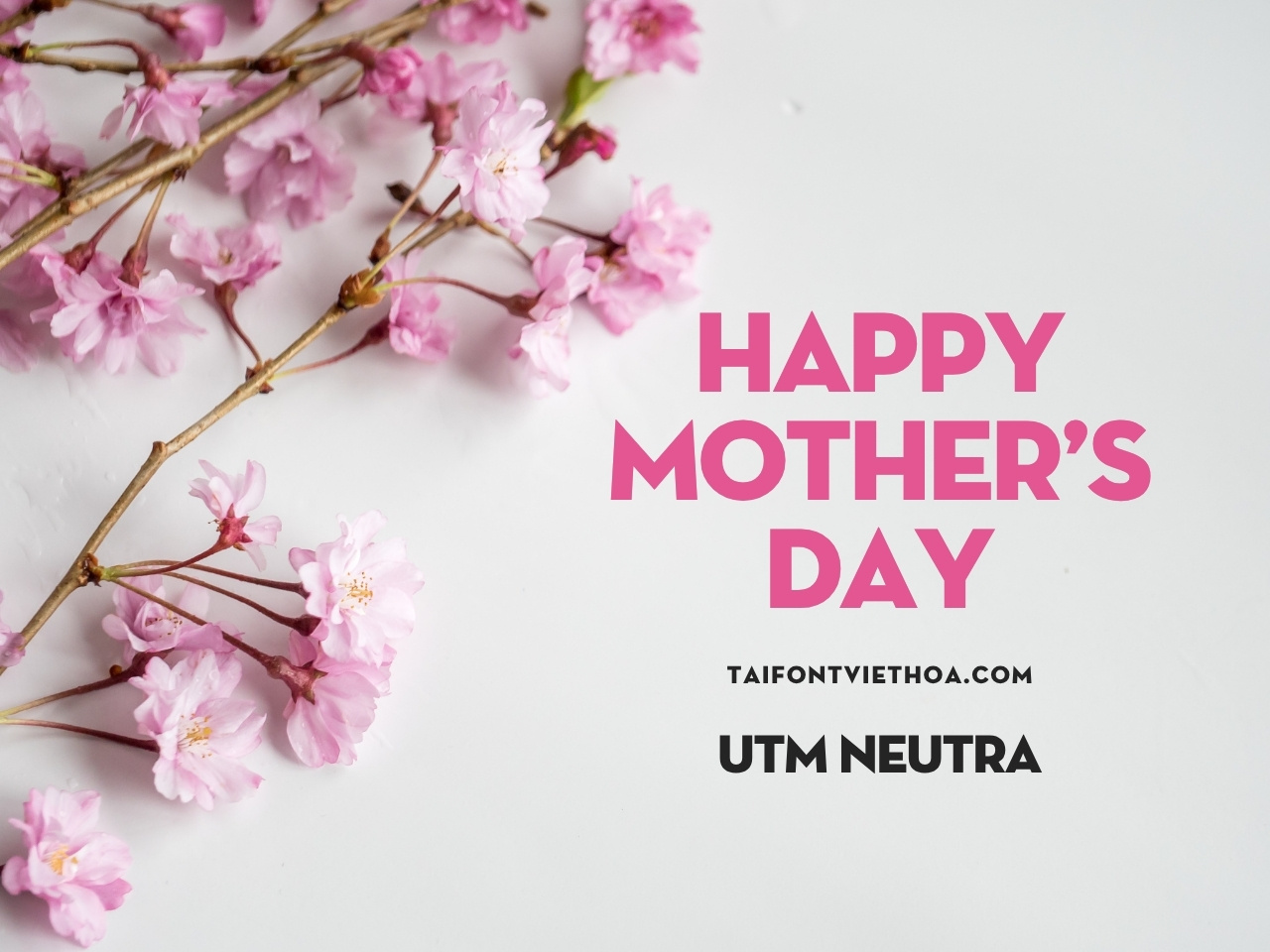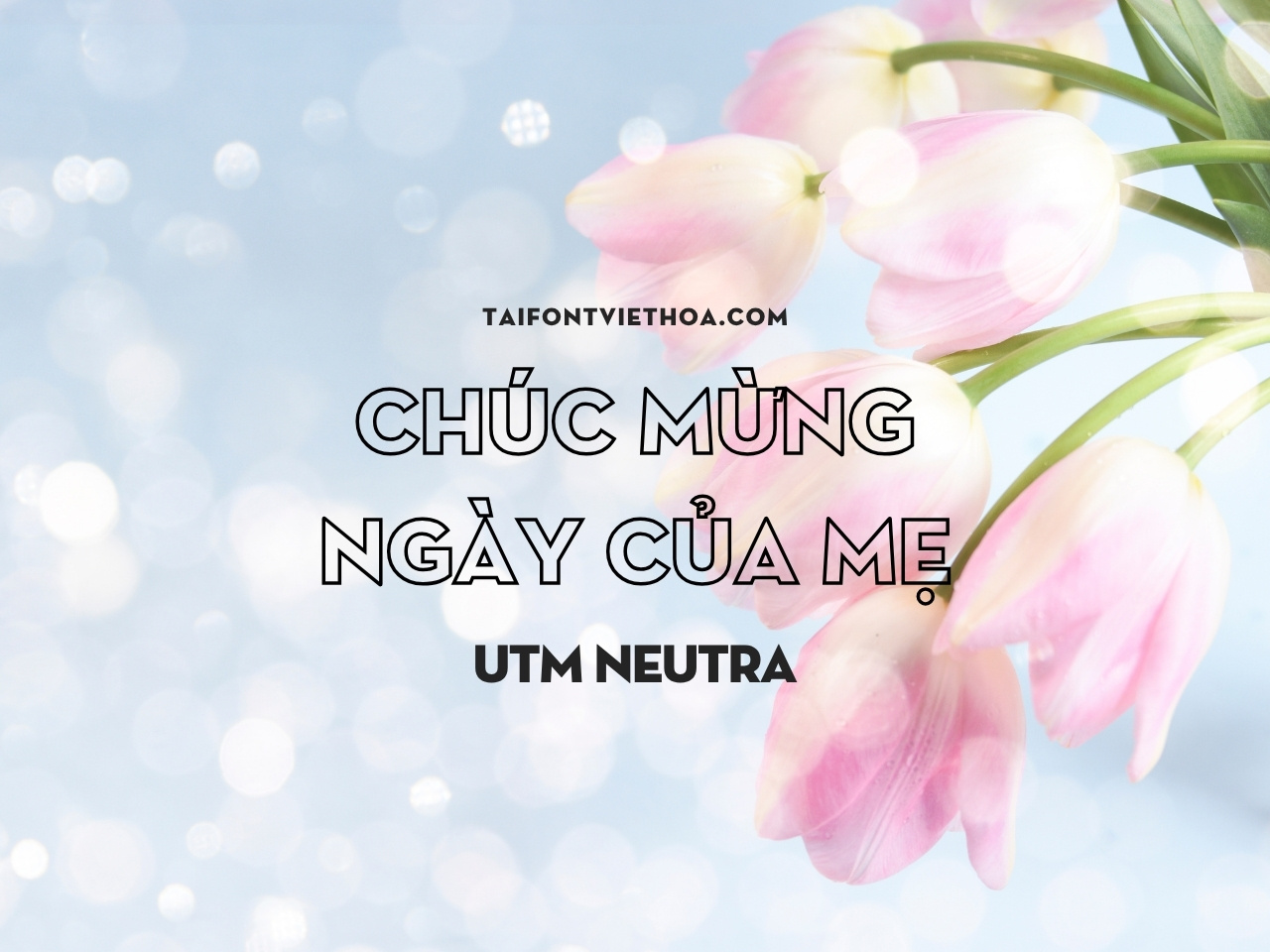
Giới thiệu về font UTM Neutra
UTM Neutra là phiên bản Việt hóa của font Neutra – một kiểu chữ sans-serif hiện đại, tinh tế và thanh lịch, được lấy cảm hứng từ phong cách kiến trúc Bauhaus nổi tiếng. Font gốc nổi bật với các nét chữ hình học, cân đối và tối giản, rất phù hợp cho các dự án thiết kế chuyên nghiệp và sáng tạo. Phiên bản Việt hóa đã được hoàn thiện để hỗ trợ đầy đủ tiếng Việt cùng hơn 200 ngôn ngữ khác, mở rộng khả năng sử dụng trong nhiều lĩnh vực thiết kế và truyền thông.
Font UTM Neutra được taifontviethoa.com sưu tầm và lựa chọn kỹ càng nhằm phục vụ cộng đồng thiết kế Việt Nam. Phiên bản Việt hóa giữ nguyên nét hiện đại và tinh tế của bản gốc, đồng thời tối ưu khả năng hiển thị tiếng Việt, rất phù hợp cho các dự án branding, quảng cáo và truyền thông đa phương tiện.
Đặc điểm thiết kế và ứng dụng của UTM Neutra
UTM Neutra sở hữu cấu trúc sans-serif không chân, với các nét chữ rõ ràng, đồng đều và thiết kế tối giản. Font có nhiều biến thể trọng lượng, giúp các nhà thiết kế linh hoạt sử dụng trong nhiều bối cảnh từ tiêu đề nổi bật đến nội dung chi tiết. Thiết kế font mang lại cảm giác hiện đại, chuyên nghiệp và dễ đọc trên nhiều nền tảng.
Font thích hợp sử dụng trong thiết kế website, nhận diện thương hiệu, quảng cáo, bao bì sản phẩm, brochure, poster và các dự án truyền thông đa phương tiện. Các ngành nghề phù hợp gồm: công nghệ, giáo dục, quảng cáo, startup và thương mại điện tử.